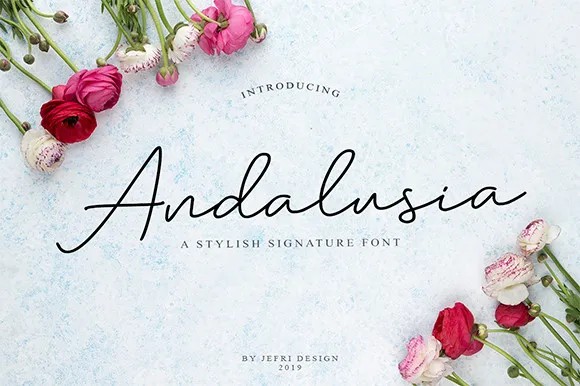
Andalusia Script Font – Download Grátis
A sua próxima descoberta no mundo das fuentes manuscritas é Andalusia Script Font, criada pelo designer bluestype. Com um toque delicado e uma simplicidade encantadora, essa fonte script tem um ar romântico que promete fazer seu trabalho de forma única. Além disso, ela possui uma genuína autenticidade, o que a torna ideal para qualquer projeto de design que deseje incorporar um toque delicado e sofisticado. Ideal tanto para nomes comerciais quanto para letras do topo de página ou textos interativos em websites, Andalusia Script Font é uma escolha perfeita para quem busca um estilo elegante e autêntico para seu próximo projeto visual.